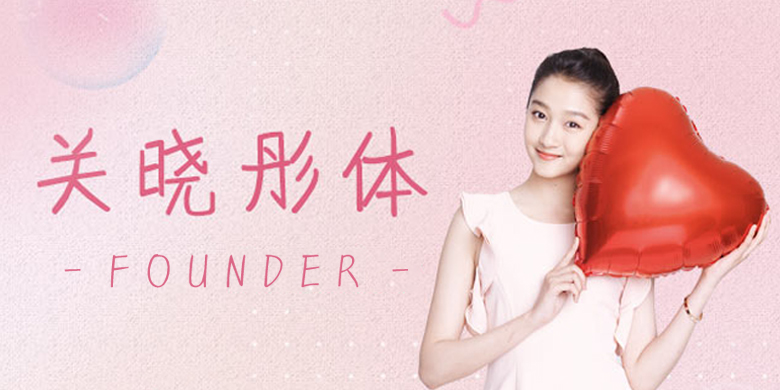
方正手迹-关晓彤体 简 关晓彤字体 方正手迹-关晓彤体 品牌: 方正手迹 设计师: 关晓彤 发行时间:2020 字库编码:大陆简体(GB2312-80) 分类:创意书写 字体属性:心动字 可爱创意书写标题正文杂志书籍广告影视电商海报包装新媒体综艺游戏动漫 方正手迹-关晓彤体,由新生代偶像女明星关晓彤所创作。其字清秀脱俗,婷婷玉立,字如其人。行笔简练流畅,结字中正平和,有良好的阅读体验。适用于现代诗歌、短文的排版以及文化、商业类品牌的广告语设计。 字体下载地址 官方下载